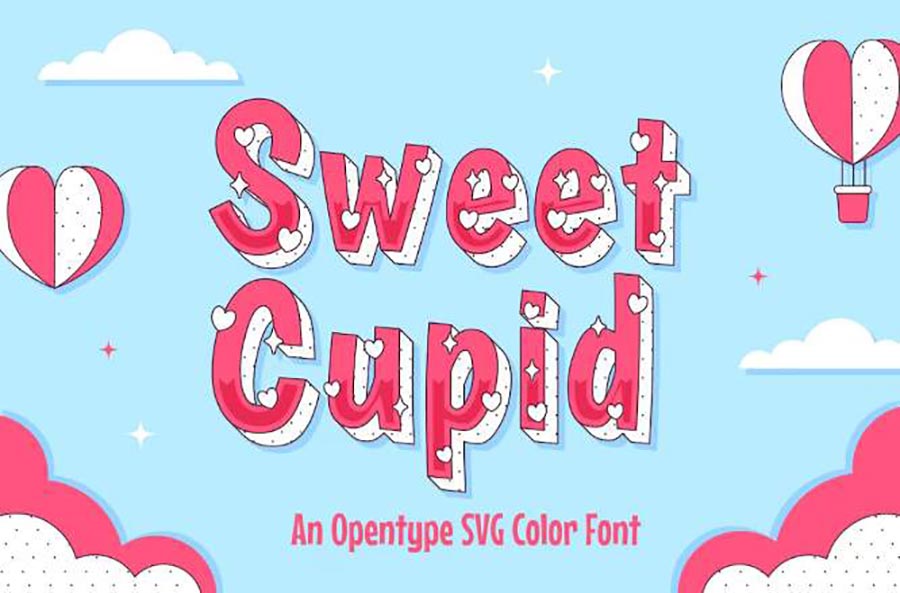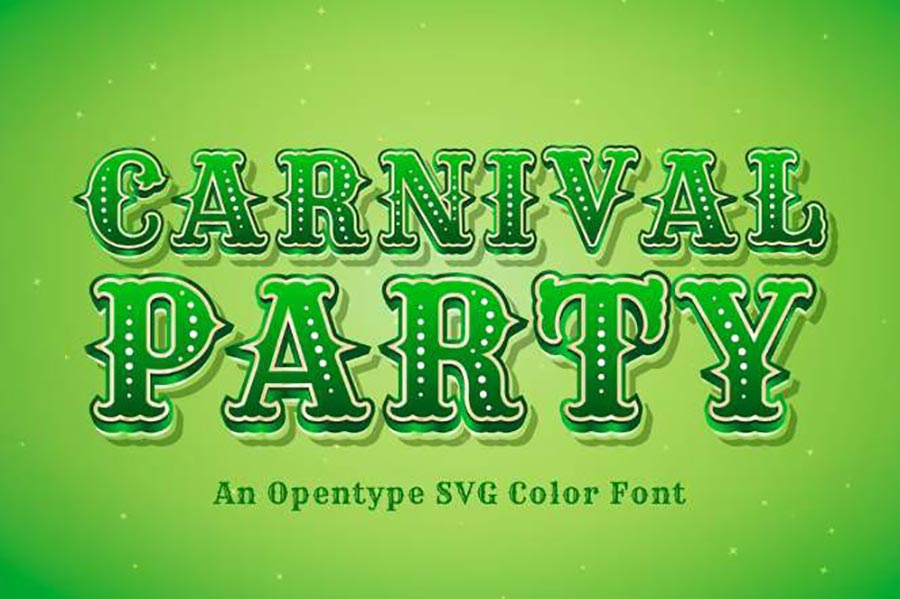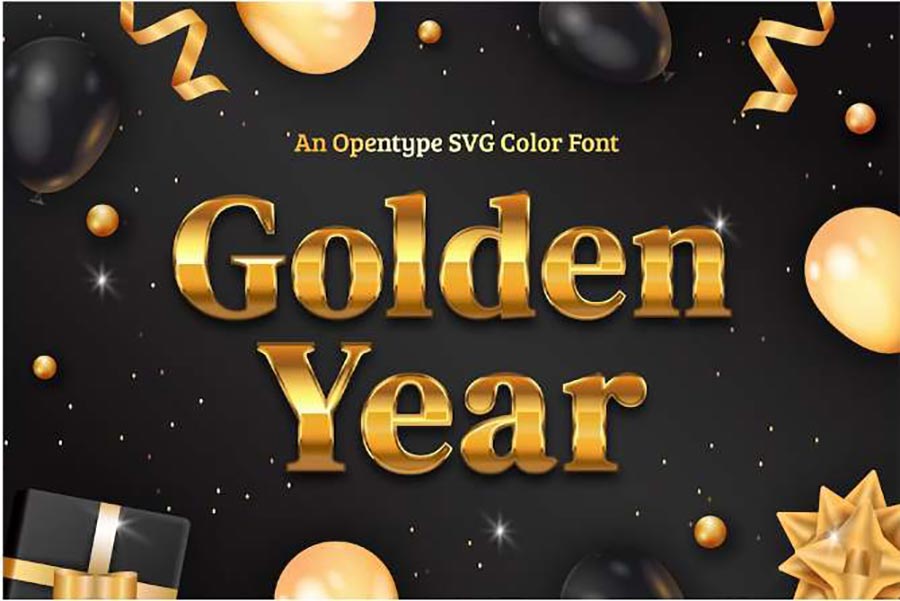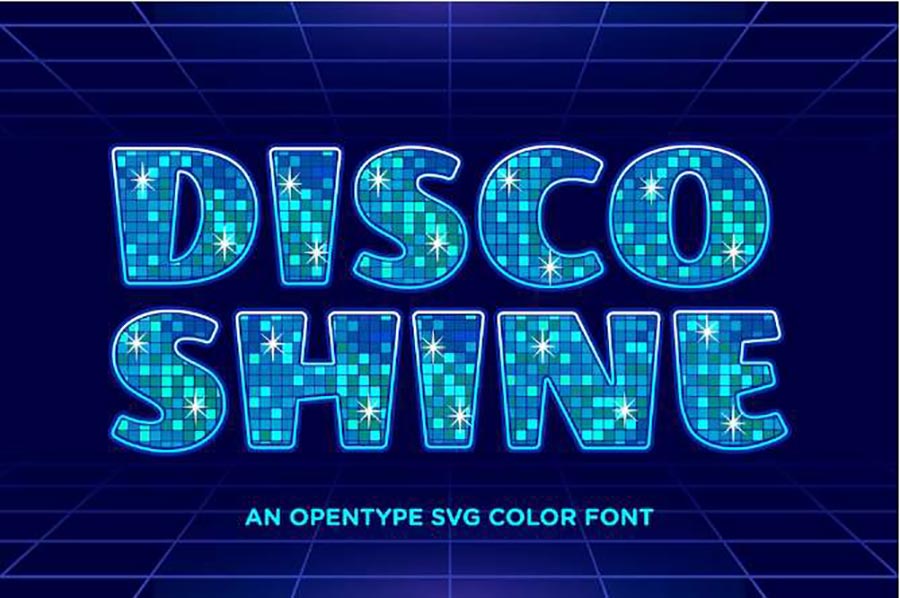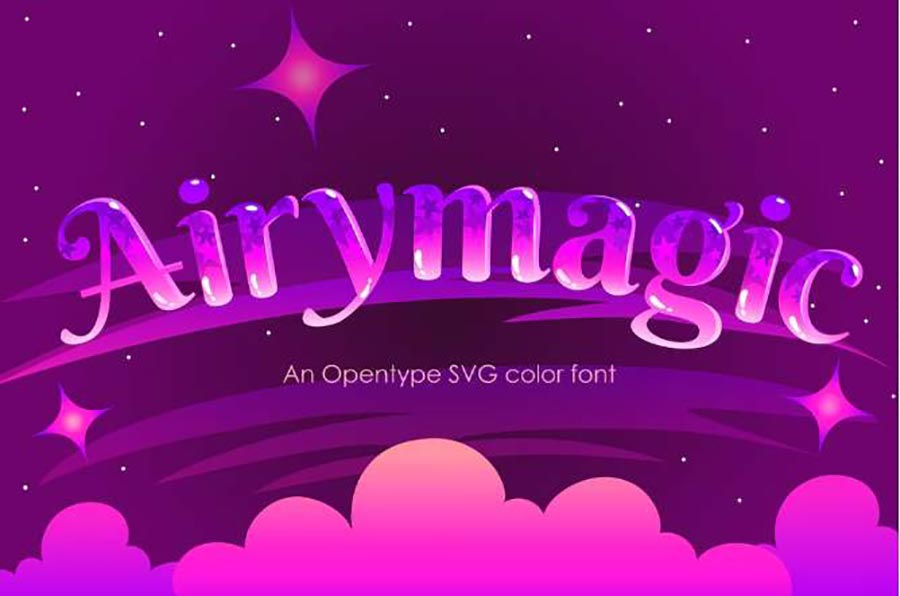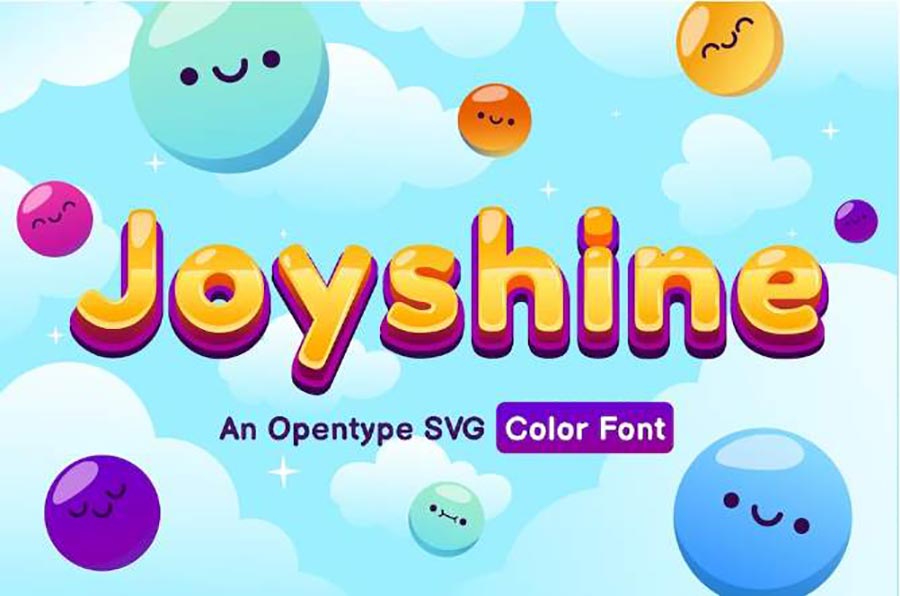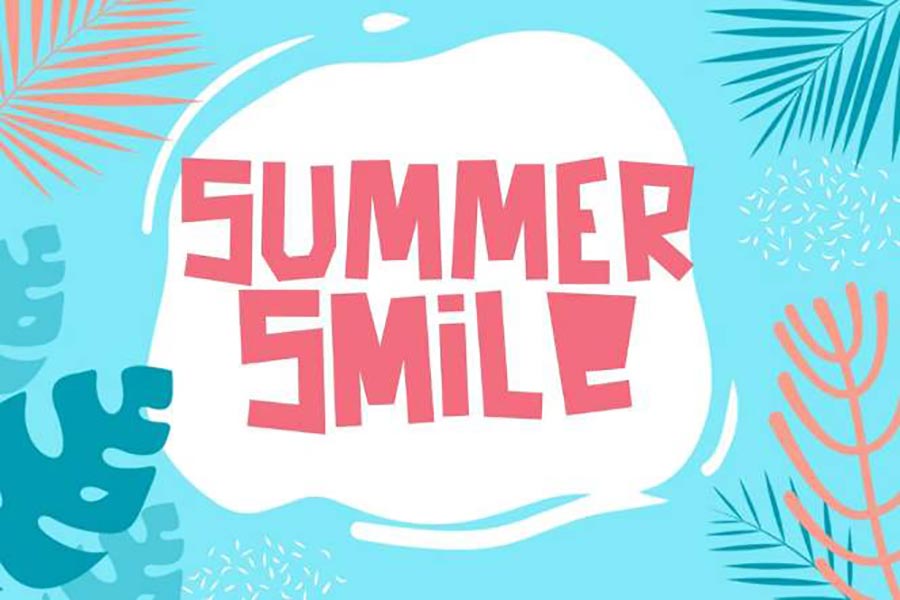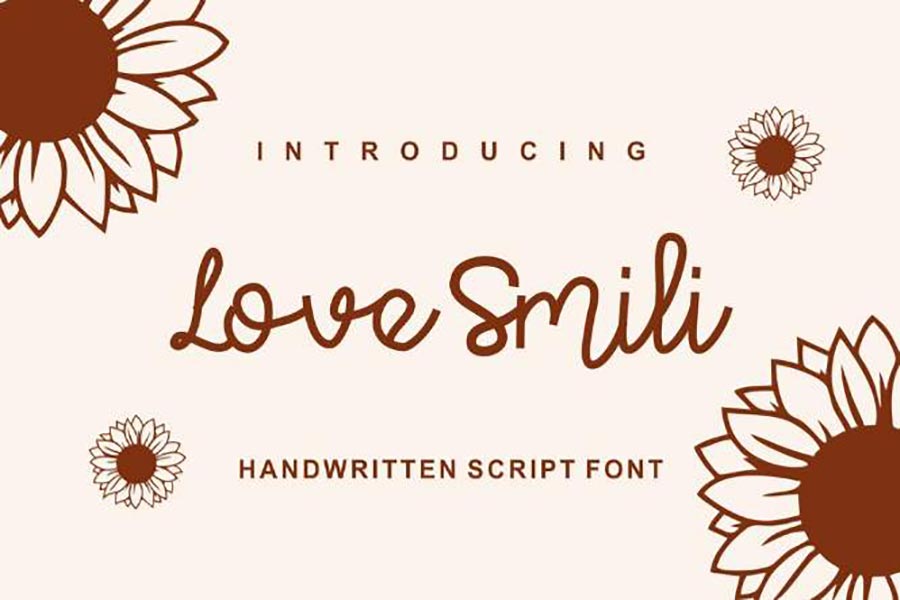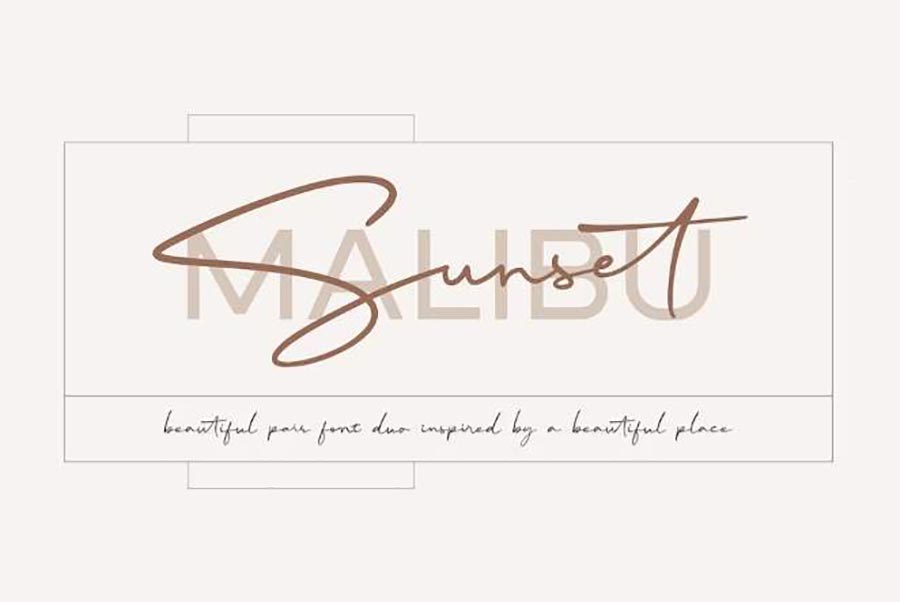
Chia Sẻ Tải Bộ 10+Fonts Happy Đẹp, Chất Lượng Dành Cho Designer
Trong lĩnh vực thiết kế đồ họa, việc lựa chọn font chữ phù hợp không chỉ góp phần làm nổi bật ý tưởng thiết kế mà còn tạo nên giá trị thẩm mỹ và chuyên nghiệp cho sản phẩm. Hiểu được tầm quan trọng của font chữ trong quá trình sáng tạo, sadesign.vn xin giới thiệu đến bạn bộ sưu tập hơn 10 font chữ "Happy" tuyệt đẹp và chất lượng cao, phù hợp với nhiều phong cách thiết kế khác nhau.
Tại sao nên chọn bộ font "Happy"?
Font chữ "Happy" được thiết kế với phong cách vui tươi, sáng tạo, phù hợp với các dự án truyền tải thông điệp tích cực như poster sự kiện, thiệp mời, banner quảng cáo hay các sản phẩm dành cho trẻ em. Những font chữ này không chỉ nổi bật bởi tính thẩm mỹ mà còn đảm bảo chất lượng đường nét, giúp các nhà thiết kế dễ dàng ứng dụng trong nhiều loại hình dự án khác nhau.
Đặc điểm nổi bật của bộ font "Happy"
1. Đa dạng phong cách: Bộ font bao gồm nhiều kiểu dáng từ đơn giản, nhẹ nhàng đến phá cách, độc đáo, đáp ứng nhu cầu đa dạng của các designer.
2. Chất lượng cao: Các font chữ được tối ưu hóa để hiển thị rõ ràng trên cả màn hình và bản in, đảm bảo sự sắc nét và chuyên nghiệp.
4. Tính ứng dụng cao: Dễ dàng sử dụng trong các dự án thiết kế thương mại hoặc cá nhân.
Danh sách một số font nổi bật trong bộ sưu tập
- Happy Times: Font chữ mang phong cách vui nhộn, phù hợp cho các thiết kế dành cho trẻ em.
- Cheerful Script: Phong cách chữ viết tay mềm mại, lý tưởng cho thiệp mời hoặc thiết kế mang tính cá nhân.
- Bubble Joy: Font chữ tròn trịa, đáng yêu, thường được sử dụng trong các banner quảng cáo hoặc thiết kế sản phẩm.
- Sunny Days: Một lựa chọn hoàn hảo cho các thiết kế mang phong cách thiên nhiên, tươi mới.
Việc sử dụng đúng font chữ không chỉ giúp truyền tải thông điệp một cách hiệu quả mà còn nâng cao giá trị thẩm mỹ cho dự án thiết kế. Bộ font "Happy" mà sadesign.vn chia sẻ chắc chắn sẽ là nguồn cảm hứng tuyệt vời cho các designer trong hành trình sáng tạo của mình. Hãy thử ngay hôm nay và mang đến sự khác biệt cho các tác phẩm của bạn.